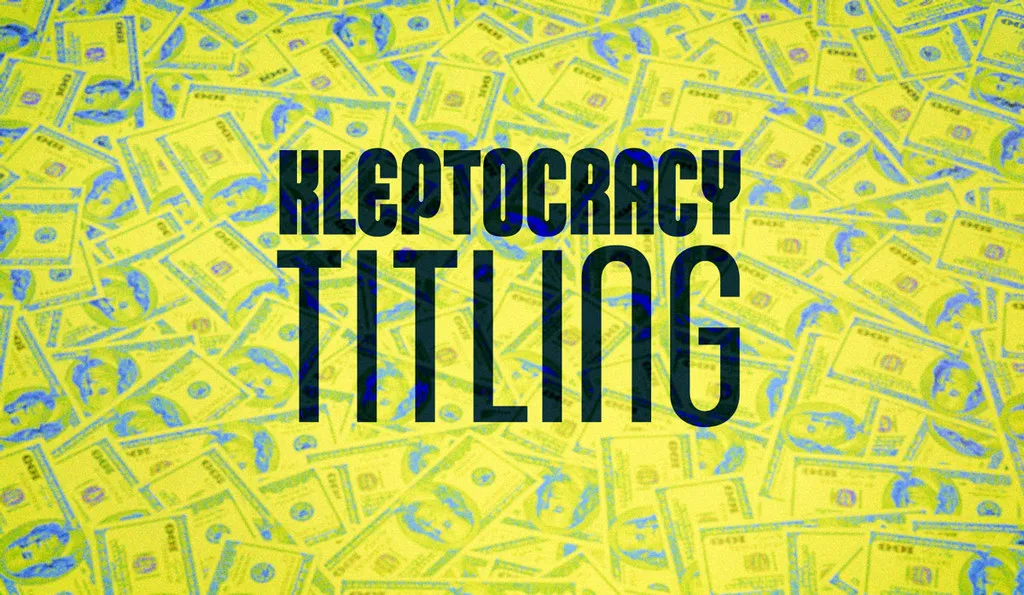
A fonte Kleptocracy Titling Font Family é a escolha perfeita para quem busca uma combinação única de eficiência industrial e curvas suaves e delicadas. Esta fonte está projetada especificamente para letras maiúsculas, oferecendo um toque calmo em sua escrita, mesmo nas situações mais exigentes e pressionantes. Com a Kleptocracy, você obtém uma versão sem serif totalmente gratuita que traz uma sensação de elegância suavizada ao formato industrial de seu texto. Essa é uma opção ideal para designers que buscam um equilíbrio perfeito entre força e sofisticação em suas criações visuais, tornando-a a escolha certa para criar texturas modernas sem perder o controle sobre sua mensagem. Visite typodermicfonts.com/kleptocracy/ para explorar mais detalhes sobre essa fonte única. Esta fonte é especialmente adequada para aplicações que exigem um equilíbrio entre eficiência e delicadeza, como design editorial, criação de gráficos informativos ou até mesmo em materiais de propaganda. Ela oferece uma maneira perfeita de destacar títulos sem perder a essência funcional e robusta do formato industrial, garantindo que o seu texto seja tanto um destaque quanto uma fonte confiável para qualquer aplicação visual. O Kleptocracy Titling Font Family é a escolha ideal para quem busca uma fonte sinérgica, onde cada traço reflete não apenas a funcionalidade necessária, mas também o desejo de tornar sua mensagem ainda mais poderosa e sofisticada.